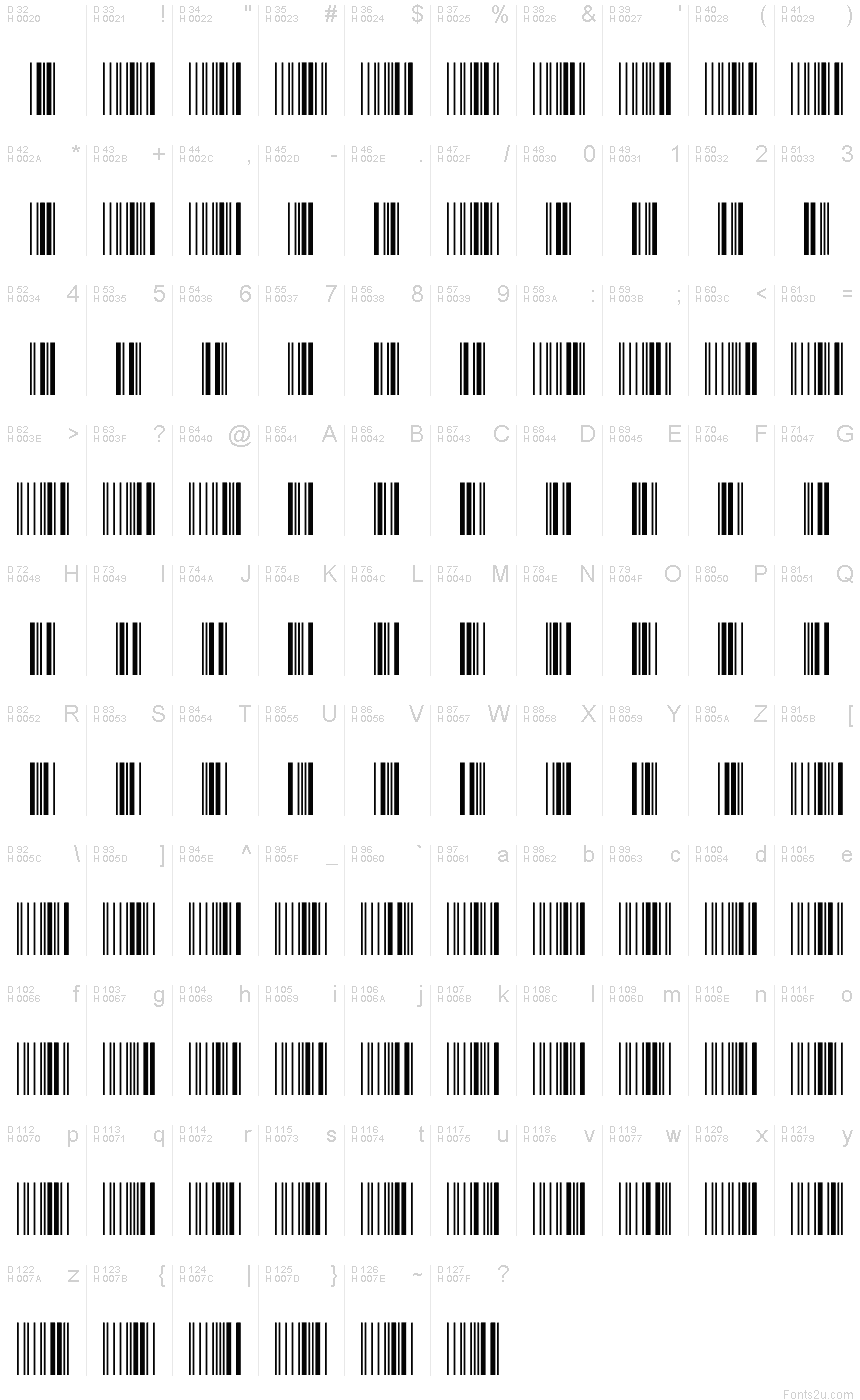
Free 3 of 9 Extended von Matthew Welch ist eine kostenlose Barcode-Schrift, die auf dem vertrauten Rhythmus der schmalen und breiten vertikalen Balken des Code 39 basiert. Die Buchstaben bilden klare Abfolgen von Streifen und Lücken, was ihr ein sachliches Erscheinungsbild verleiht – eher wie Verpackungsmarkierungen, Inventar-Labels oder maschinenlesbare Grafiken als wie dekoratives Ornament.
Sie passt perfekt in Retail-Mockups, Lagerbeschilderungen, Produktverpackungen, Versandetiketten und Requisitengrafiken für Interfaces oder Filmtitel, bei denen eine industrielle Codierungs-Note die Szenerie abrundet. Als kostenlose Schrift eignet sie sich zudem hervorragend für kurze Schlagzeilen, Sticker-Designs und Posterdetails, besonders wenn man die grafische Wirkung von Barcode-Balken anstelle klassischer Schriftzeichen sucht.
Free 3 of 9 Extended